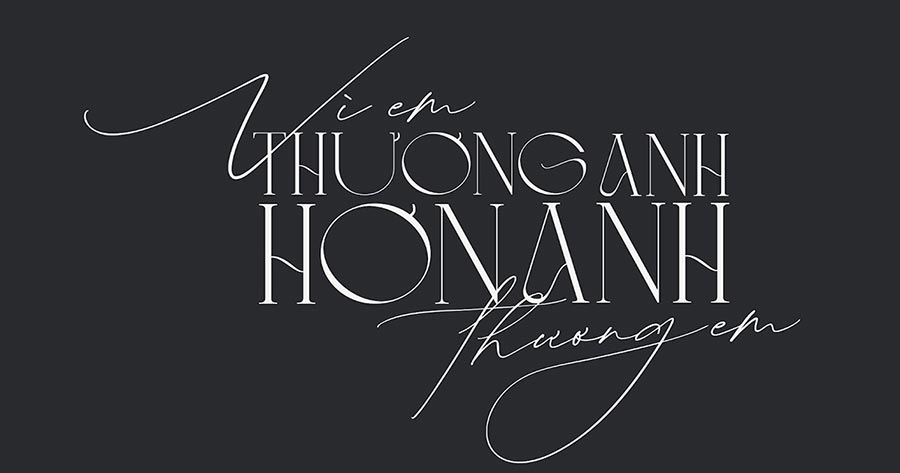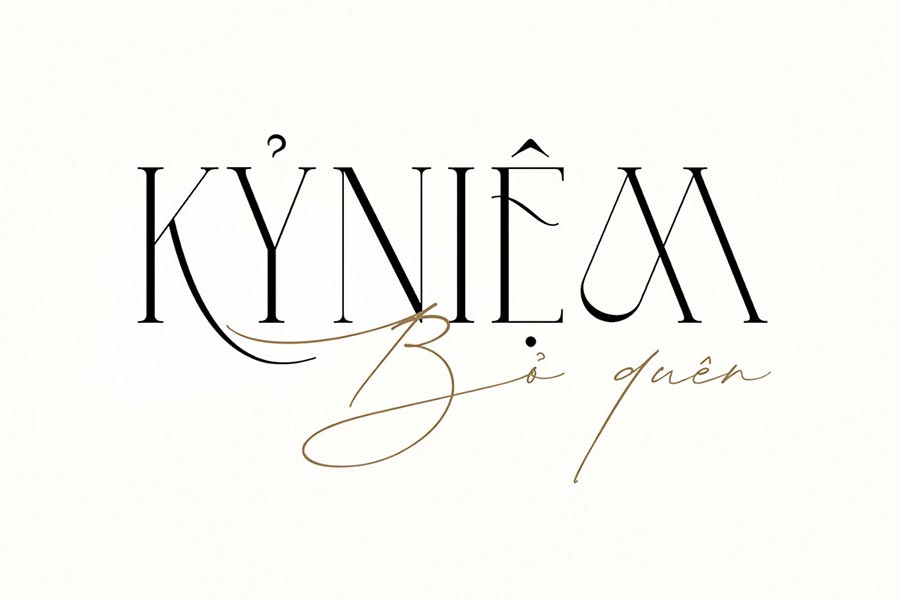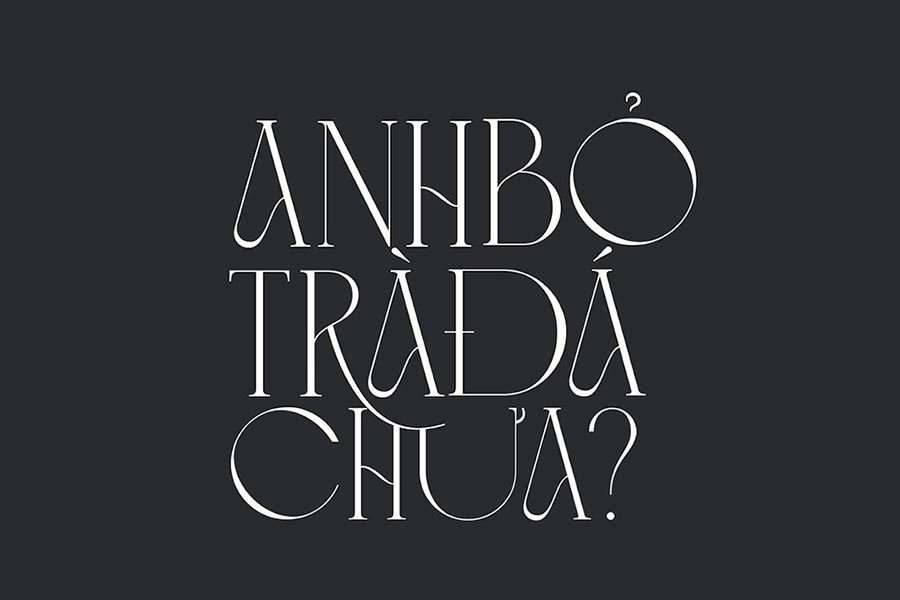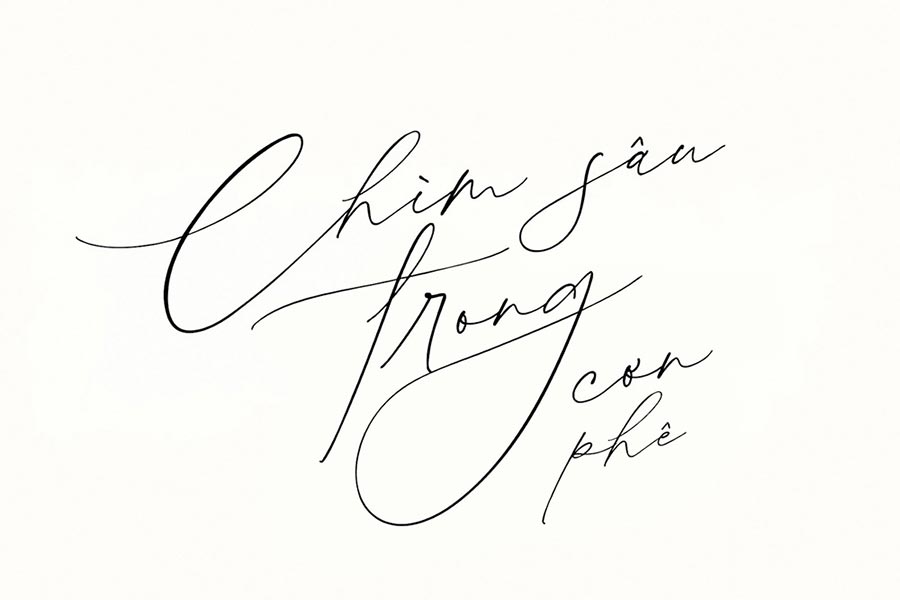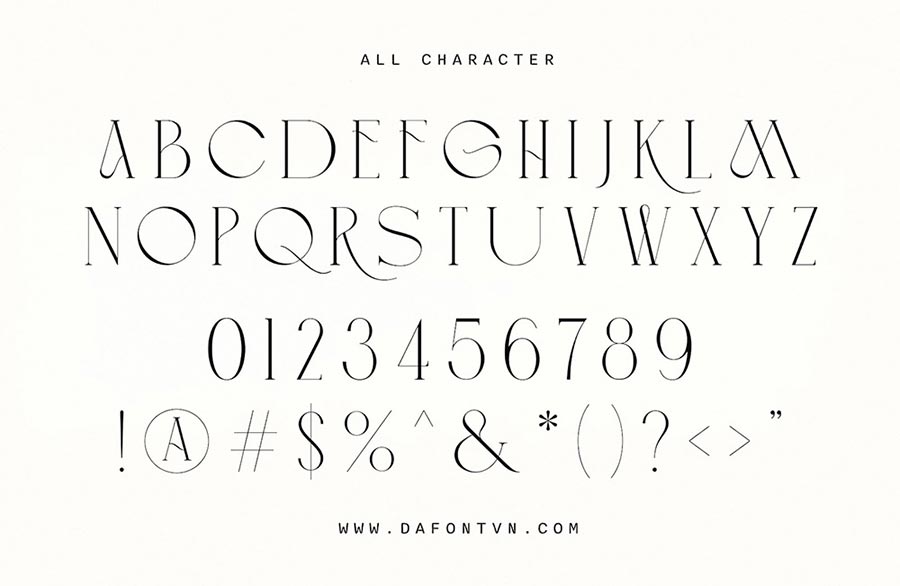
Chia Sẻ Miễn Phí Font Việt Hóa - Simple Serenity Mang Phong Cách Hiện Đại Và Cổ Điển
Font chữ luôn là một yếu tố quan trọng trong thiết kế đồ họa, ảnh hưởng trực tiếp đến cảm nhận thẩm mỹ và thông điệp của sản phẩm. Với sự kết hợp hài hòa giữa hiện đại và cổ điển, font Việt hóa Simple Serenity do sadesign.vn chia sẻ miễn phí chắc chắn sẽ là lựa chọn hoàn hảo cho các nhà thiết kế đang tìm kiếm sự độc đáo và tinh tế.
Font Simple Serenity – Sự Giao Thoa Giữa Hai Phong Cách
Font Simple Serenity mang trong mình vẻ đẹp của sự tối giản hiện đại, đồng thời gợi lên nét cổ điển thanh lịch qua từng chi tiết. Được thiết kế một cách tỉ mỉ, font chữ này không chỉ phù hợp cho các dự án thiết kế hiện đại mà còn tạo điểm nhấn đặc biệt cho các sản phẩm mang hơi hướng vintage.
Phong cách hiện đại của Simple Serenity được thể hiện qua các đường nét gọn gàng, sắc sảo, tạo cảm giác chuyên nghiệp và dễ đọc. Trong khi đó, các chi tiết bo tròn nhẹ nhàng và độ dày chữ được cân đối kỹ lưỡng lại mang đến một cảm giác cổ điển đầy tinh tế. Sự kết hợp này giúp font chữ trở thành công cụ lý tưởng để sử dụng trong nhiều loại dự án khác nhau, từ thiết kế thương hiệu, banner quảng cáo cho đến thiệp mời hay bìa sách.
Lợi Ích Khi Sử Dụng Font Việt Hóa Simple Serenity
Hỗ Trợ Tiếng Việt Hoàn Hảo : Font Simple Serenity đã được Việt hóa hoàn chỉnh, hỗ trợ đầy đủ các dấu câu và ký tự tiếng Việt.
Tính Ứng Dụng Cao: Font này phù hợp với nhiều lĩnh vực như thời trang, mỹ phẩm, nội thất hay thậm chí là các sản phẩm công nghệ.
Tăng Tính Thẩm Mỹ Cho Thiết Kế: Simple Serenity giúp các thiết kế của bạn nổi bật hơn, thu hút sự chú ý của người xem ngay từ cái nhìn đầu tiên.
Font Việt hóa Simple Serenity là một lựa chọn tuyệt vời dành cho những ai đang tìm kiếm sự kết hợp hoàn hảo giữa phong cách hiện đại và cổ điển trong thiết kế. Với chất lượng cao, tính ứng dụng linh hoạt và đặc biệt là hoàn toàn miễn phí, đây chắc chắn sẽ là một công cụ không thể thiếu trong bộ sưu tập của bất kỳ nhà thiết kế nào.